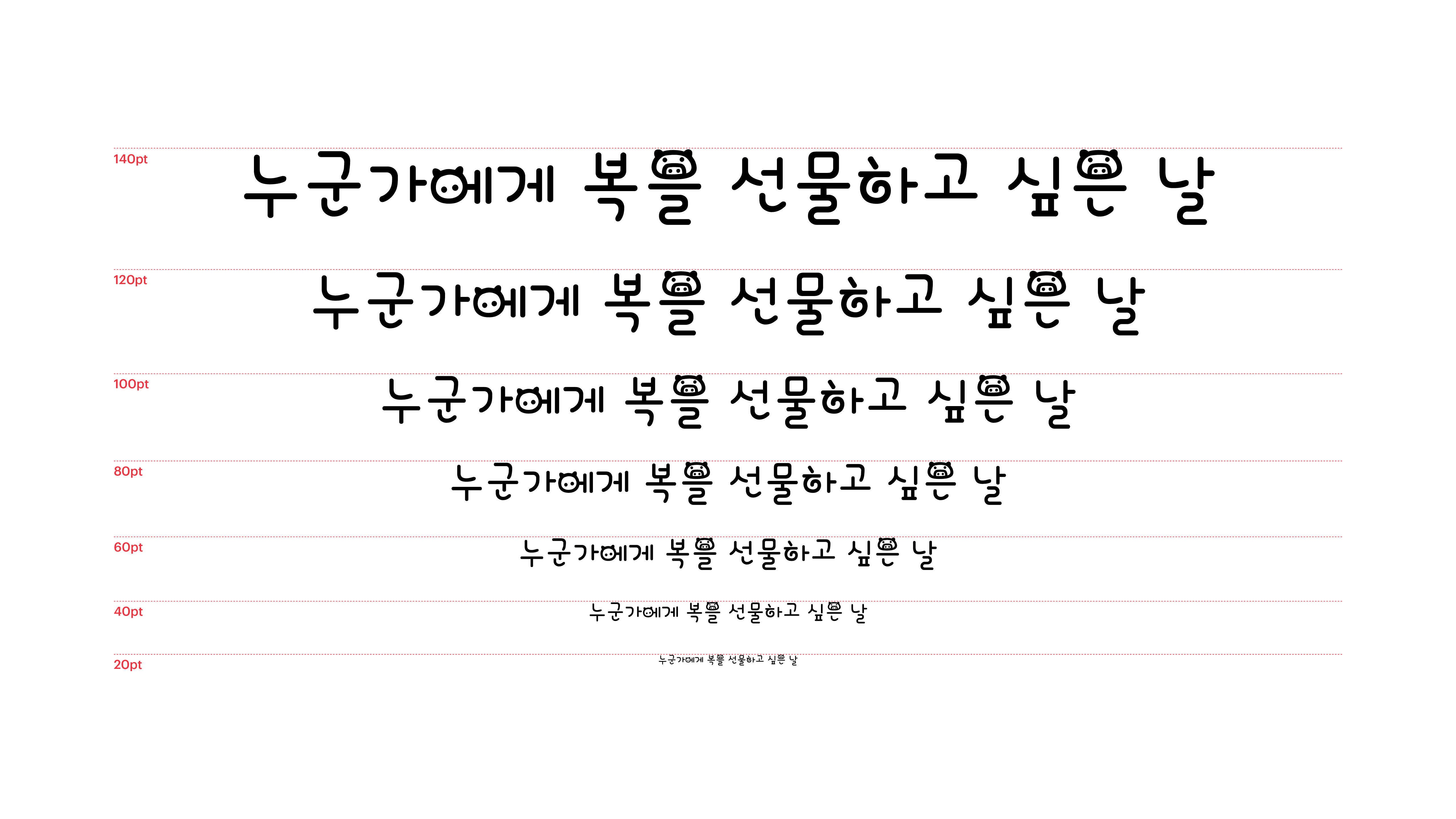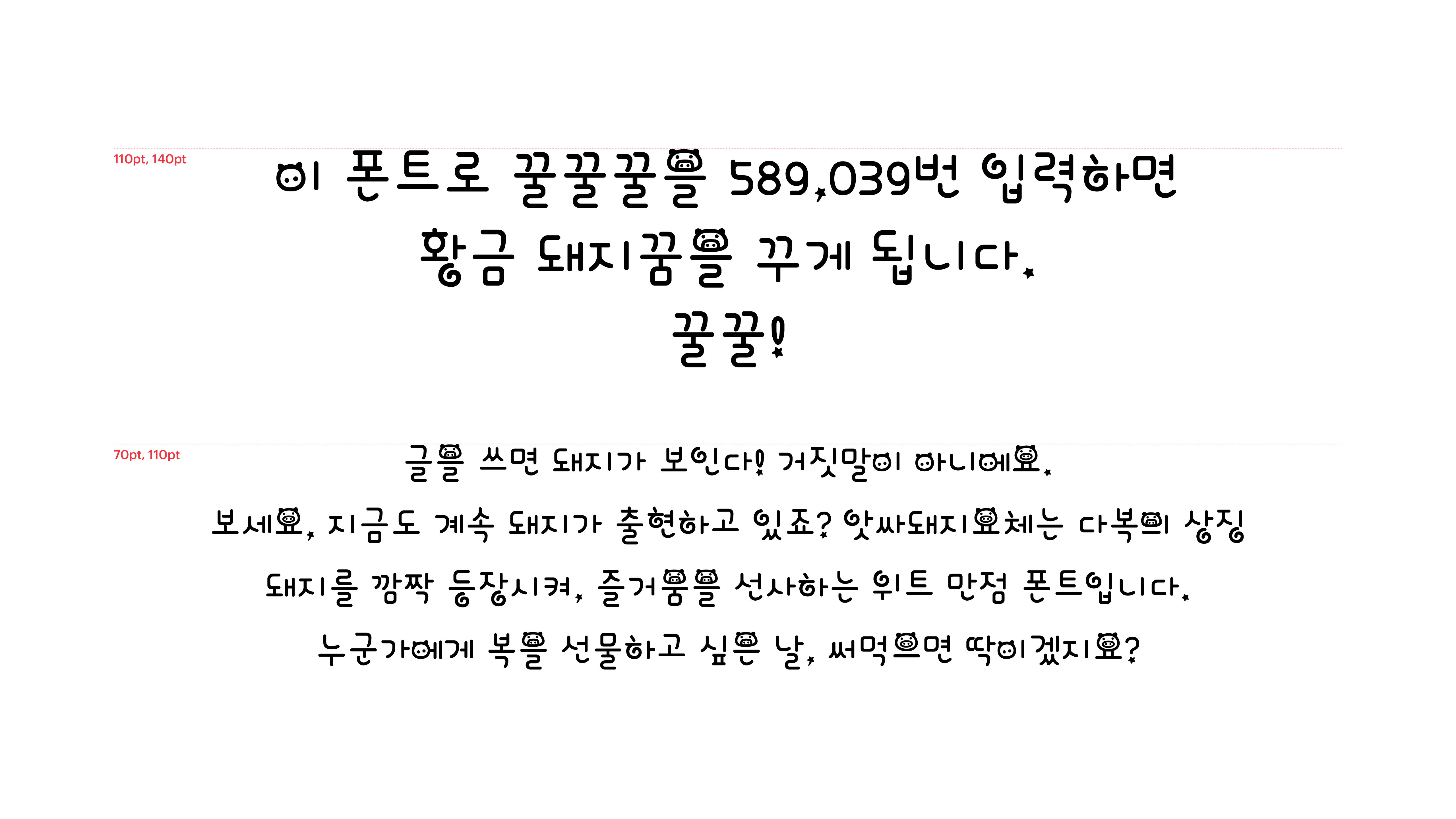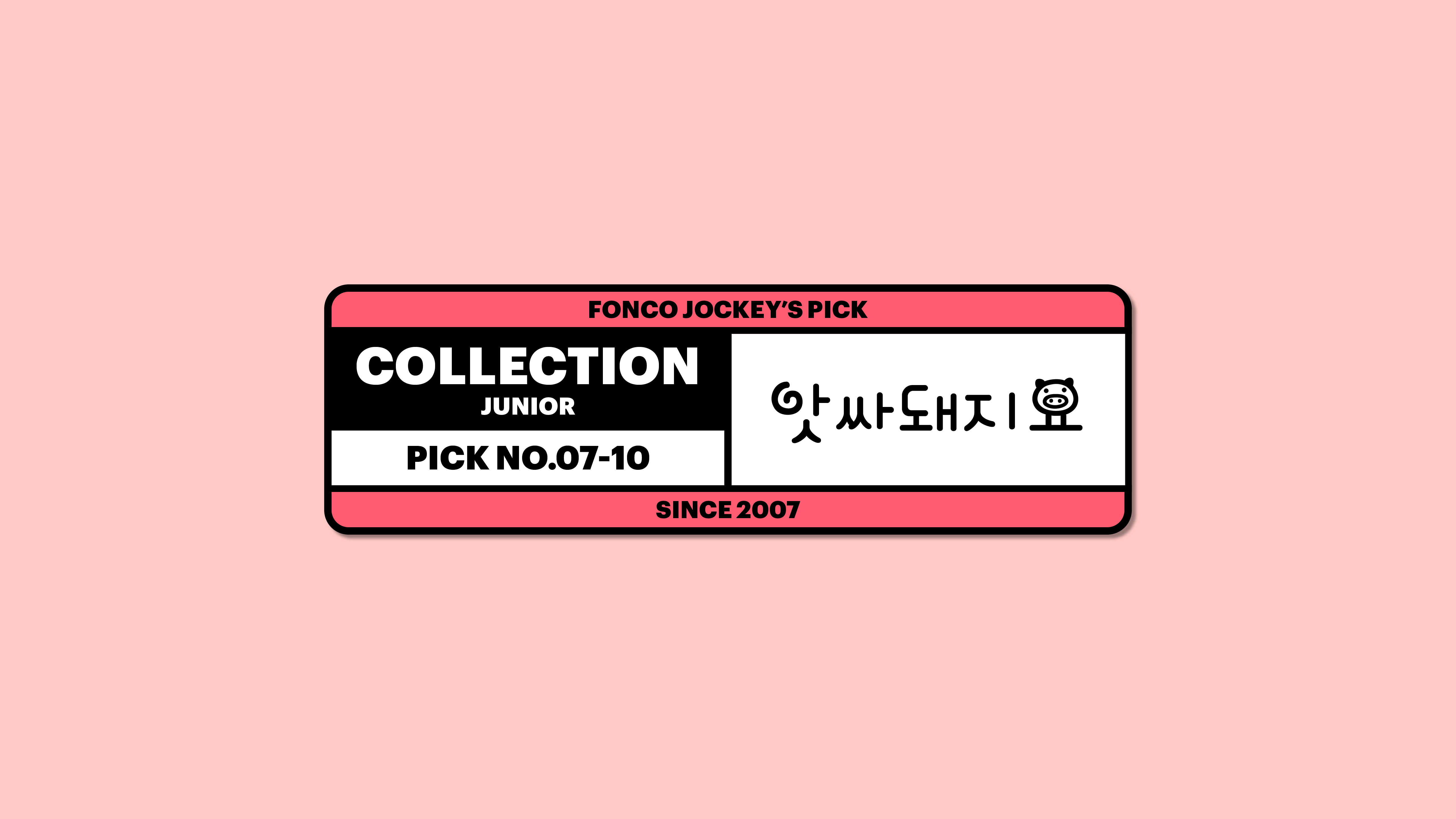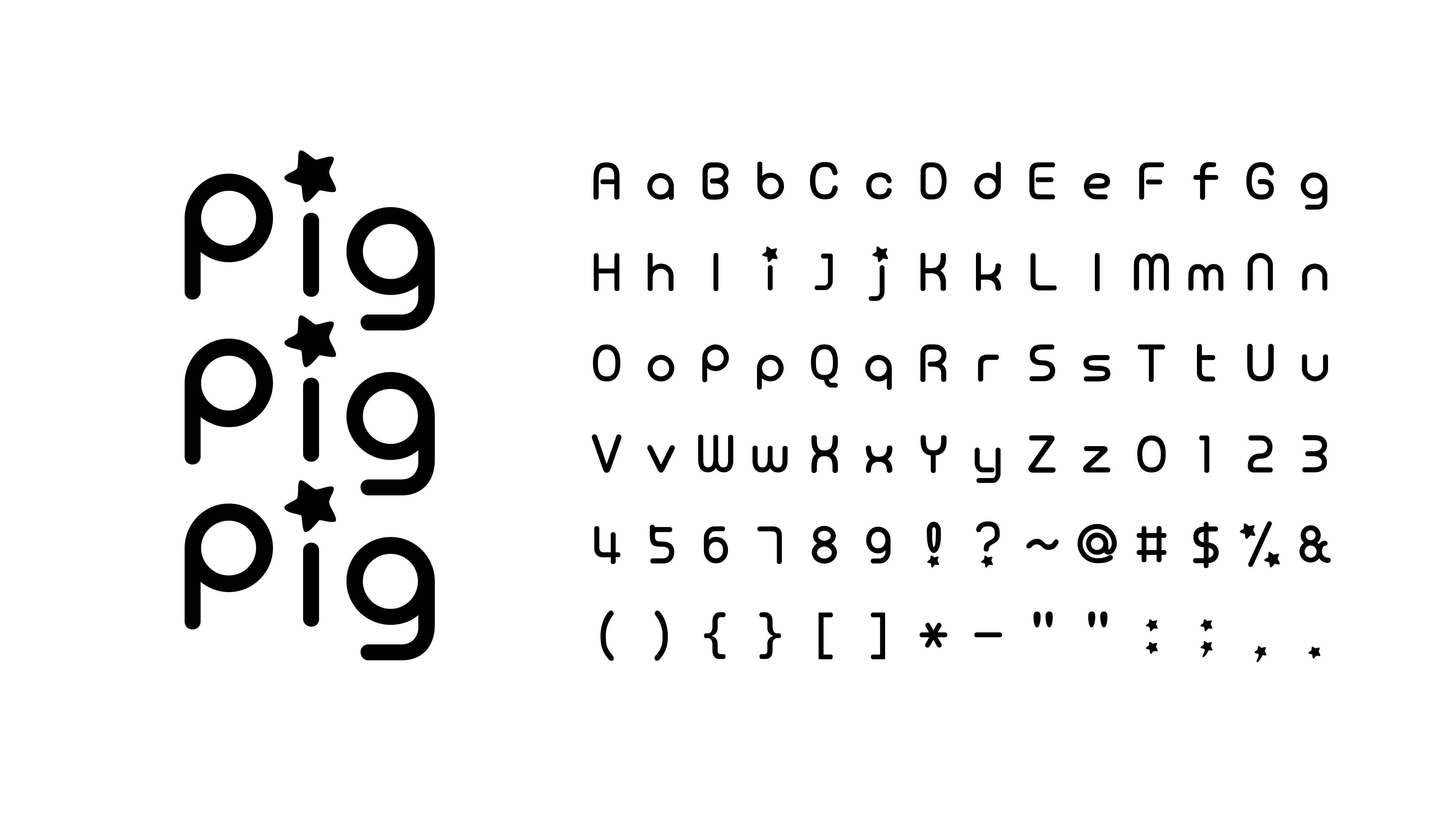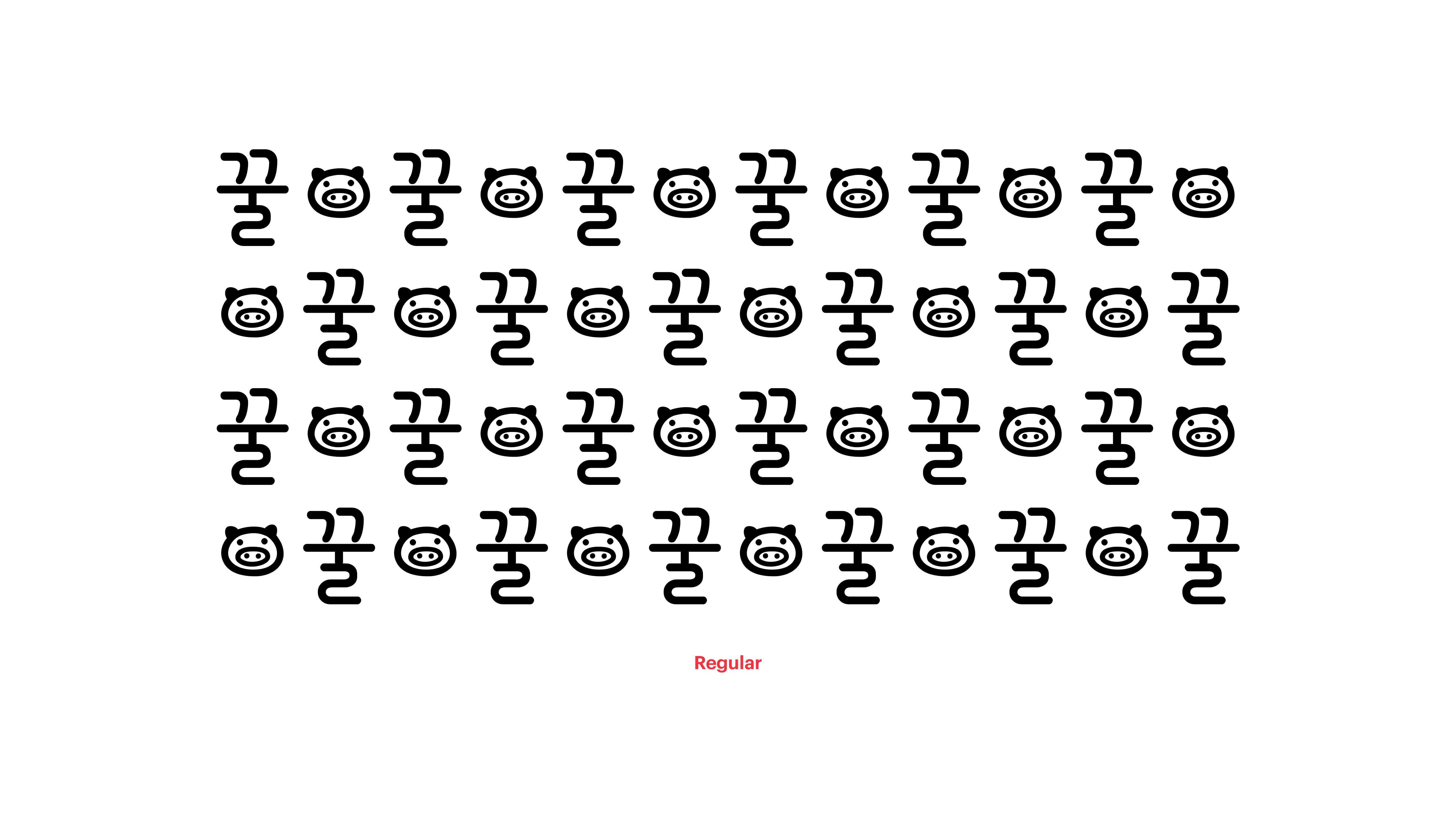
앗싸돼지요
Yoon 앗싸돼지요
글을 쓰면 돼지가 보인다! 거짓말이 아니에요. 보세요, 지금도 계속 돼지가 출현하고 있죠? 앗싸돼지요체는 다복의 상징 돼지를 깜짝 등장시켜, 즐거움을 선사하는 위트 만점 폰트입니다. 누군가에게 복을 선물하고 싶은 날, 써먹으면 딱이겠지요?